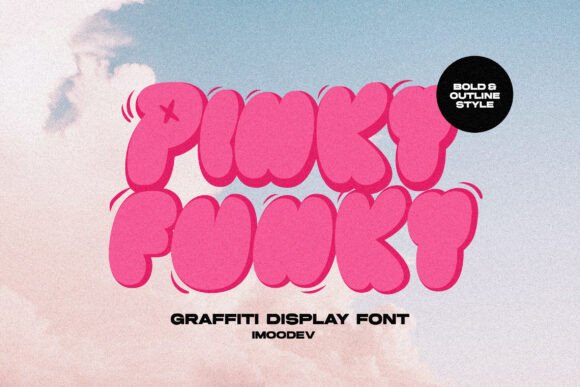
Pinky Funky
適切なデザイン要素を見つけるのは難しい場合がありますが、Pinky Funkyは作品を即座に引き立てる優れたコレクションを提供します。
POD(オンデマンド印刷)製品、結婚式の招待状、またはソーシャルメディアのグラフィックを作成している場合でも、Pinky Funkyは理想的です。